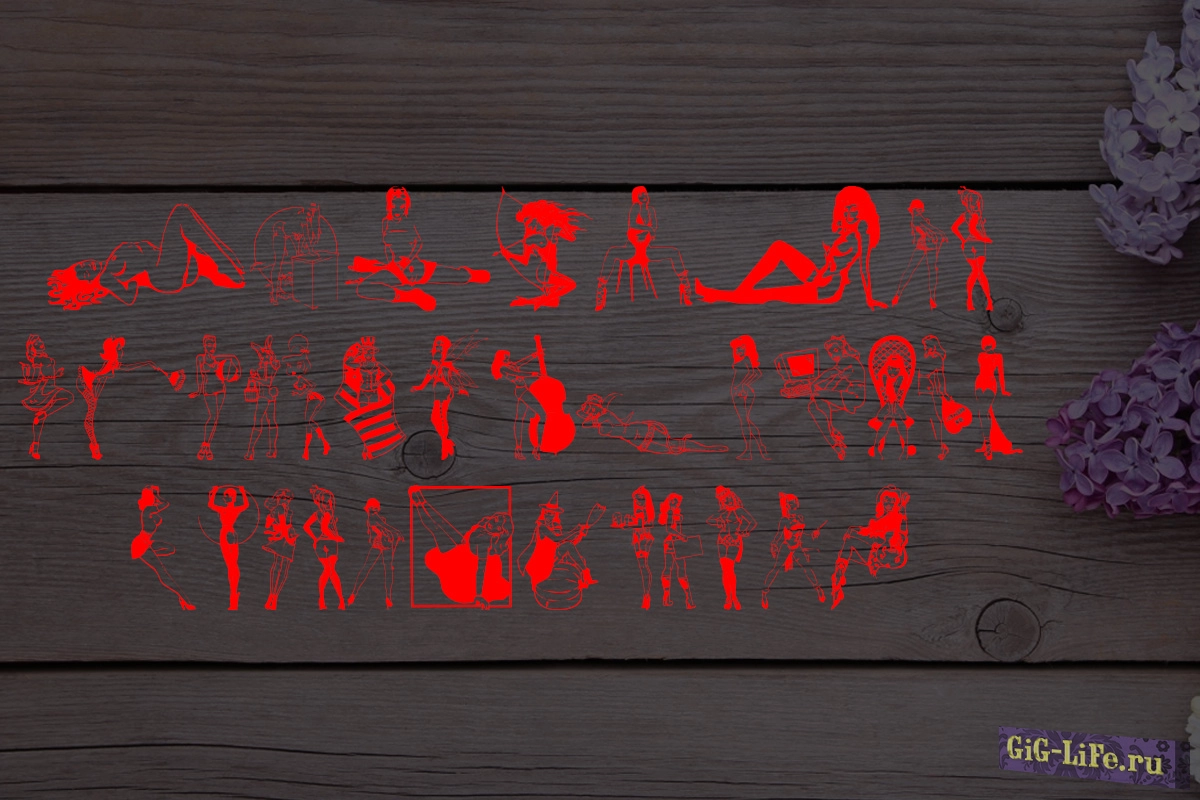
Шрифт — Beauties by Bill Ward
Шрифт Beauties by Bill Ward – идеальное решение для создания эротической атмосферы в Photoshop и других графических проектах. Этот шрифт идеально подойдет для уникального оформления и подчеркнет сексуальность ваших работ.